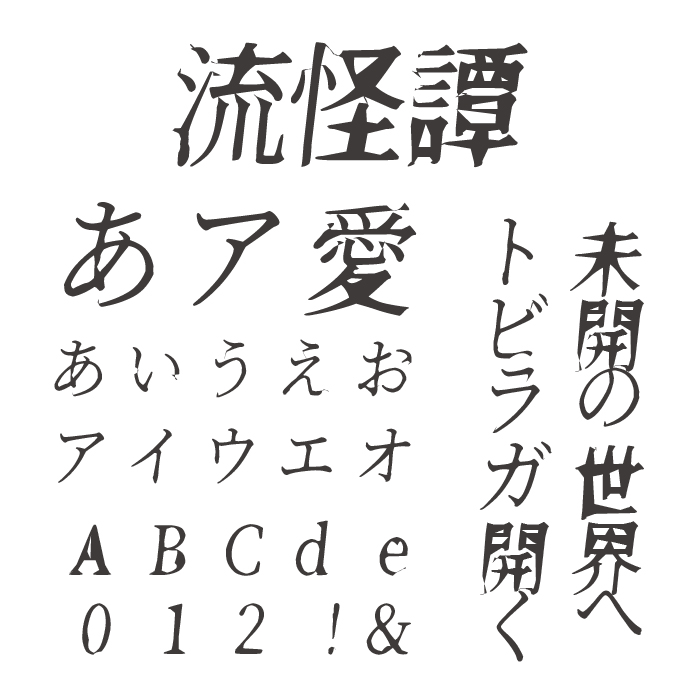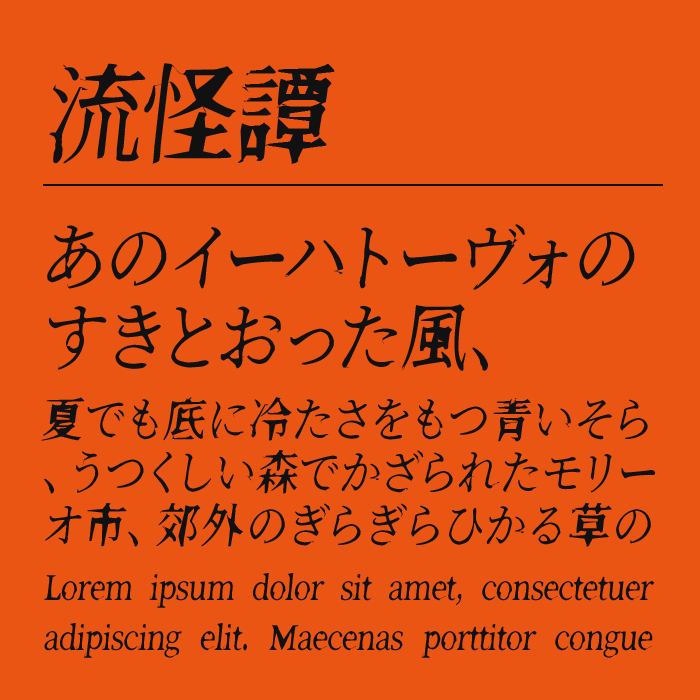
流怪譚フォントは、明朝体ベースで、筆文字の崩し方に、どこか「不気味さ」や「怪しさ」を纏わせた独特なフォントです。
筆の流れが強調された流麗な線でありながら、通常の行書体や草書体とは異なり、画線の太さやバランスが意図的に不安定にされており、文字の形が溶けたり歪んだりしているような印象のあるフォントです。「ただの崩し文字ではない」異様な雰囲気が最大の魅力です。
ミステリアス、ホラー、あるいは幻想的な世界観を表現したいときに真価を発揮します。 例えば、怪談話の表紙、ホラーゲームのタイトルロゴ、謎解きイベントのポスターなど、「非日常的な、ゾクッとする美しさ」を伝えたい場面にぴったりです